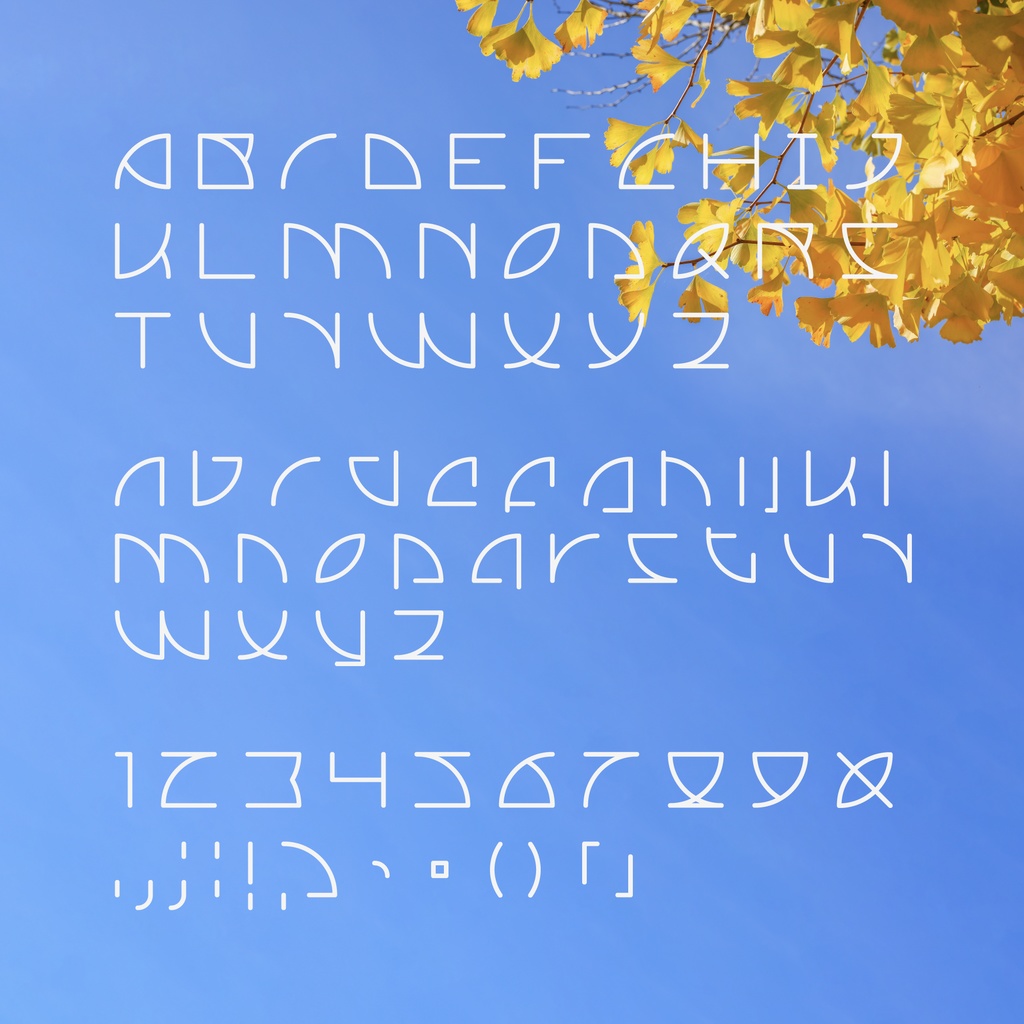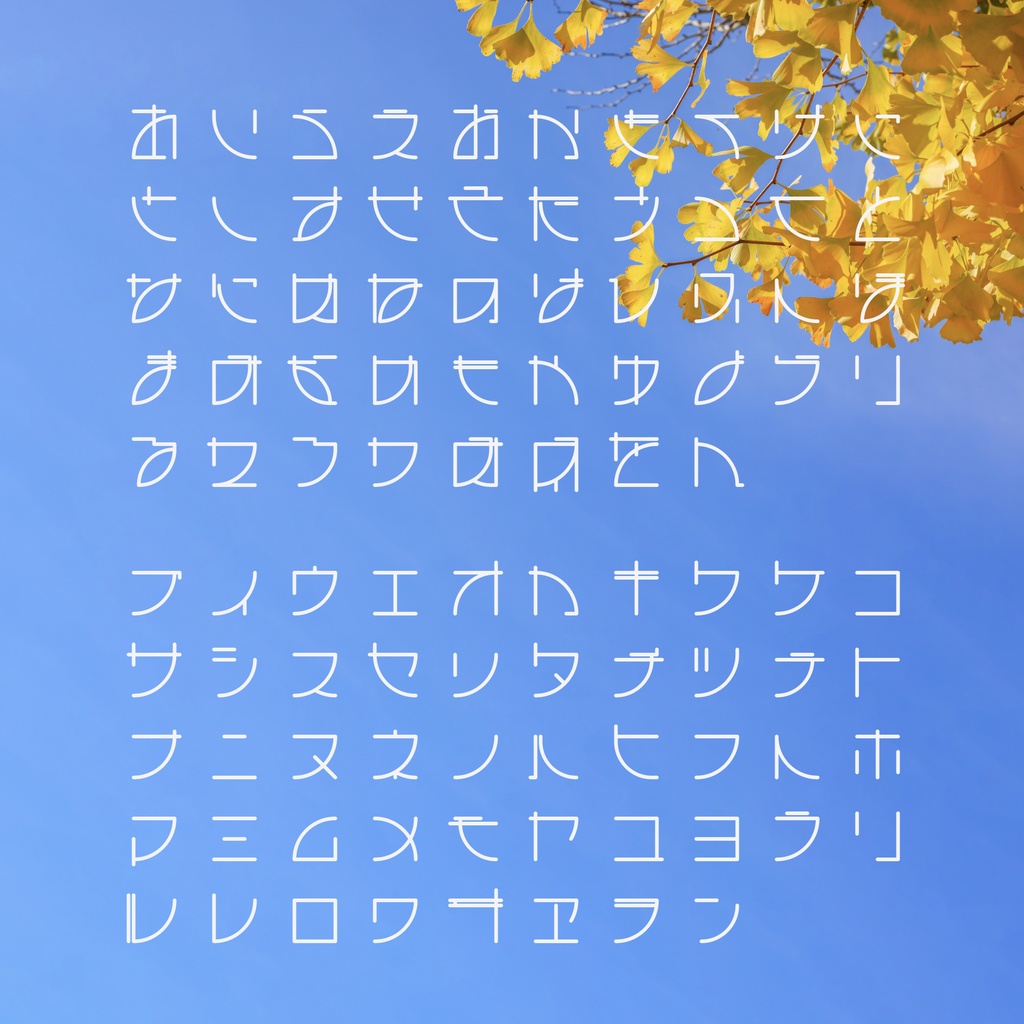
Amari Font Challenge 100-50 仮名実装 📢📢📢特記事項📢📢📢 100日フォントチャレンジ無事完了 この後、この100フォントに仮名を追加することに挑戦します。 英語よりも仮名の理解度が低いので、間違いがあれば遠慮なく教えてください、改善します! 有料にするか迷ったため、有料か無料かの選択肢を開放しています。 📢デザイン説明 一部の筆画を円弧に置き換えるて文字の空間感やリズム感を強調のフォント。 📢利用規約 個人、商用どちらでも利用可能です。 ✨✨✨もしもこのフォントが使用されたら、https://twitter.com/amari_designに教えていただけるとうれしいです!✨✨✨ 本素材を使用した作品については、リツイートなどの形で宣伝させていただく場合があります。 フォントのインストール等の技術的なサポートはいたしません。使用して発生したと思われる如何なる問題についても、作者は責任を負わないものとします。 著作権を放棄することはありません。 商標を登録したり、作者であると主張したり、データ自体を販売または再販したりすることは禁じられています。 このコンテンツの最終的な解釈権は作者に帰属します。 内容補充とバージョン更新は製作続けるです。使用する際は最新バージョンにご注意ください。 📢収録內容 ラテン文字、数字、仮名だけてを含む263グリフが含まれています。 ーーーーーーーーーーーー Twitter:https://twitter.com/amari_design Behance:https://www.behance.net/9f45706b ーーーーーーーーーーーー